手账这一说其实来源于日本,在日本大部分人都会随身带着一个笔记本,随时翻看记录在册的一些事情。现在很多人都开始写手账,用可爱生趣的字体记录生活中的点点滴滴,提升生活幸福指数。制作一篇手账最重要的就是要用赏心悦目的字体,那有哪些适合写手账的字体呢,咱们一起来看看吧。
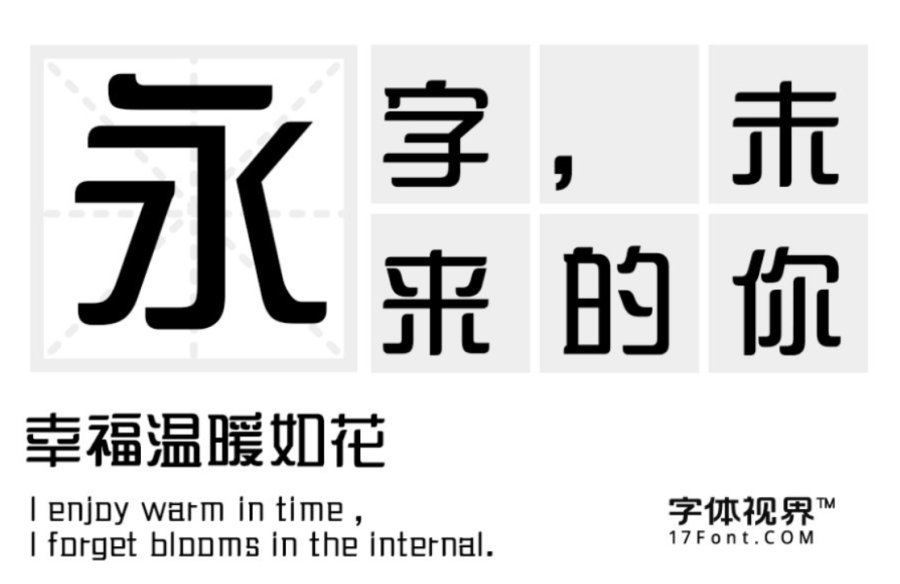
三极雅鹊简体:这款字体的起笔收笔和转折处参照的是鸟类的特征,形成鹊首圆弧的字形特点。字形清晰易于识别字体,典雅灵秀、活灵活现,仿佛一只鸟儿在树上轻轻扇动着翅膀,极具画面感。不仅适用于手账中的字体,还适用于书刊、广告、包装、影视以及社交网络的个性化用字。
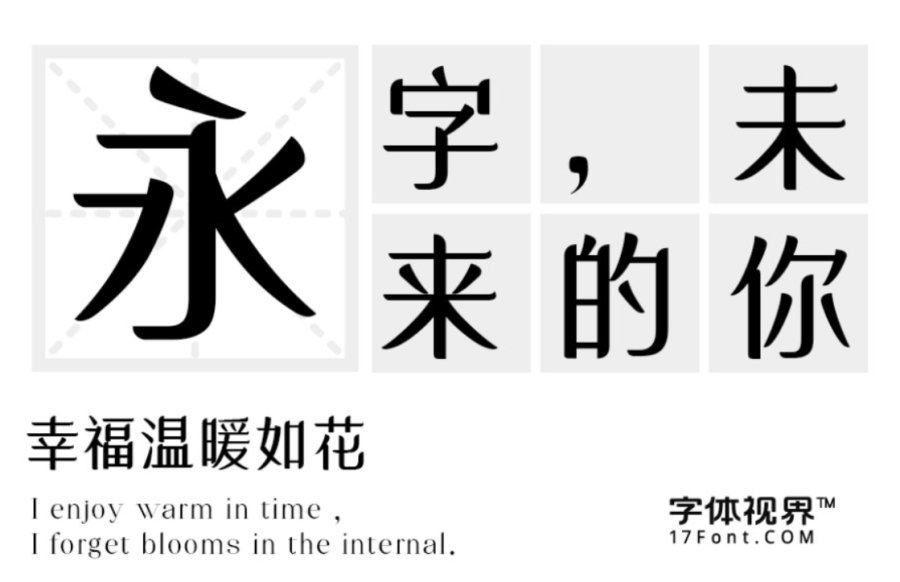
三极花信简体:这是一款具有典雅气质的风格化黑体作品。兼具了黑体的简洁和宋体的雅致特征。整体字形方正,刚柔相济,优雅大方。为手账增添了一份文艺色彩。还适用用于商业广告、书刊出版、产品包装及界面设计标题,店招牌匾等领域。
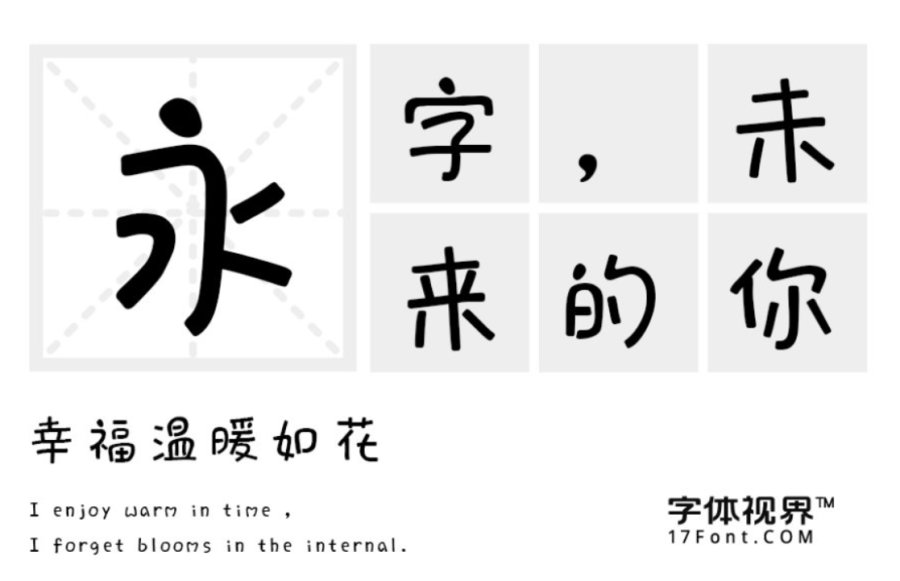
三极萌娃简体:这款字体是以儿童写字的特点,勾勒笔画,具有童稚之情。笔画圆润,字形轮廓统一,灵动可爱,溢于画笔,清新萌动。用在手账里显得格外趣智生动。还适用少儿类读物、书刊以及社交网络个性化用字等领域。